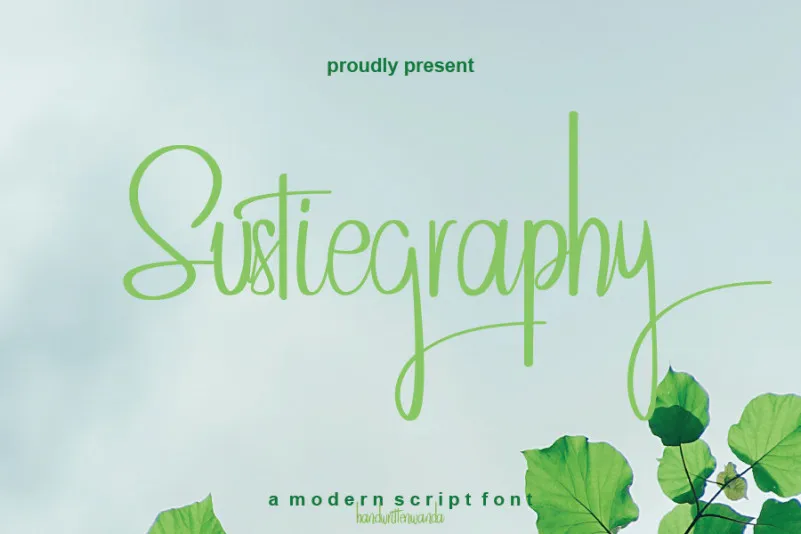
Sustiegraphy Font – Fonte Grátis
Sustiegraphy Font
A ‘Sustiegraphy Font’ é uma elegante fatura de escrita que transmite sofisticação e encanto. Desenvolvida pela designer handwrittenwanda, essa fonte é um conjunto perfeito de alternativas estilizadas e ligaturas cuidadosamente projetadas para dar um toque único a qualquer projeto. Seja em cartões de aniversário criativos ou letras decorativas em livros de arte, esta fatura manuscrita traz um ar de refinamento à sua obra. Com um design natural e fluido que evoca uma sensação de autenticidade artística, ‘Sustiegraphy Font’ é a escolha perfeita para quem busca algo mais do que apenas uma fonte: eles desejam transmitir um sentimento intimo e sofisticado através do texto.